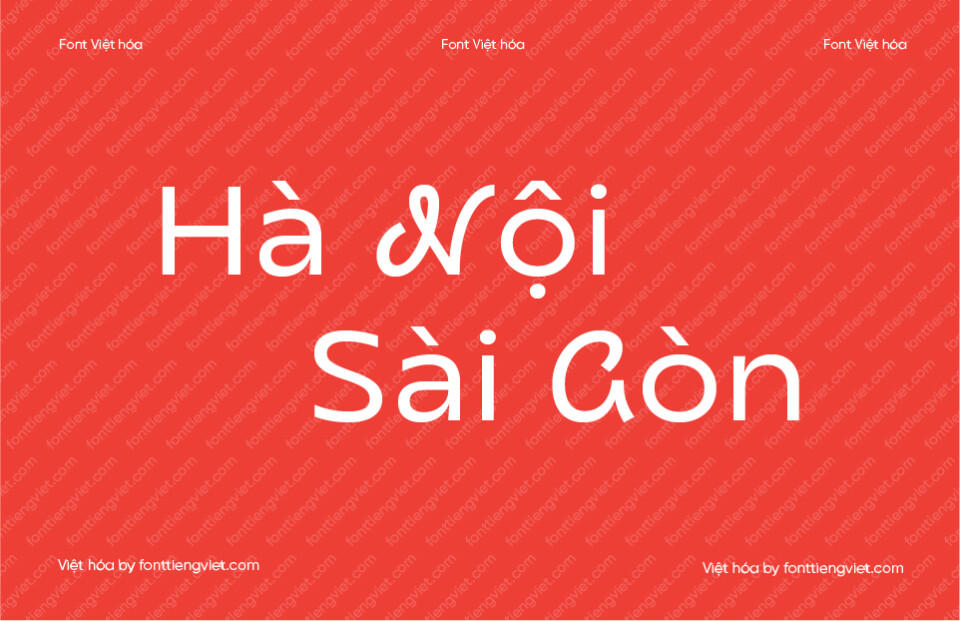
Font Việt hóa 1FTV Transforma Mix Medium
Giới thiệu về bộ Font Việt hóa 1FTV Transforma Mix Medium
Trong thế giới đồ họa hiện đại, việc lựa chọn một Font Miễn Phí chất lượng luôn là ưu tiên hàng đầu của các nhà thiết kế. Font Việt hóa 1FTV Transforma Mix Medium nổi lên như một giải pháp hoàn hảo nhờ sự kết hợp độc đáo giữa phong cách cổ điển và hơi thở đương đại. Đây là một biến thể nằm trong hệ thống phông chữ đa dạng, mang đến vẻ ngoài cứng cáp nhưng không kém phần linh hoạt cho mọi dự án sáng tạo của bạn.
Đặc điểm thiết kế của 1FTV Transforma Mix Medium
Bộ font này gây ấn tượng mạnh bởi các đường nét trung tính, giúp văn bản trở nên dễ đọc trên cả phương diện in ấn lẫn hiển thị kỹ thuật số. Với độ dày vừa phải (Medium), nó tạo ra sự cân bằng thị giác tuyệt vời, không quá mảnh mai cũng không quá đậm nét. Việc sử dụng Font Việt hóa 1FTV Transforma Mix Medium giúp người dùng truyền tải thông điệp một cách chuyên nghiệp và tinh tế hơn bao giờ hết.
Ứng dụng Font Việt hóa 1FTV Transforma Mix Medium trong học tập và công việc
Đối với các bạn học sinh và giáo viên, phông chữ này cực kỳ phù hợp để trình bày slide bài giảng hoặc làm báo cáo dự án. Sự rõ ràng của các ký tự tiếng Việt giúp nội dung trở nên trực quan, hỗ trợ quá trình tiếp thu kiến thức hiệu quả. Ngoài ra, các nhà thiết kế có thể dùng nó cho logo, bao bì sản phẩm hoặc giao diện ứng dụng di động.
Lợi ích khi sử dụng font chữ đã Việt hóa